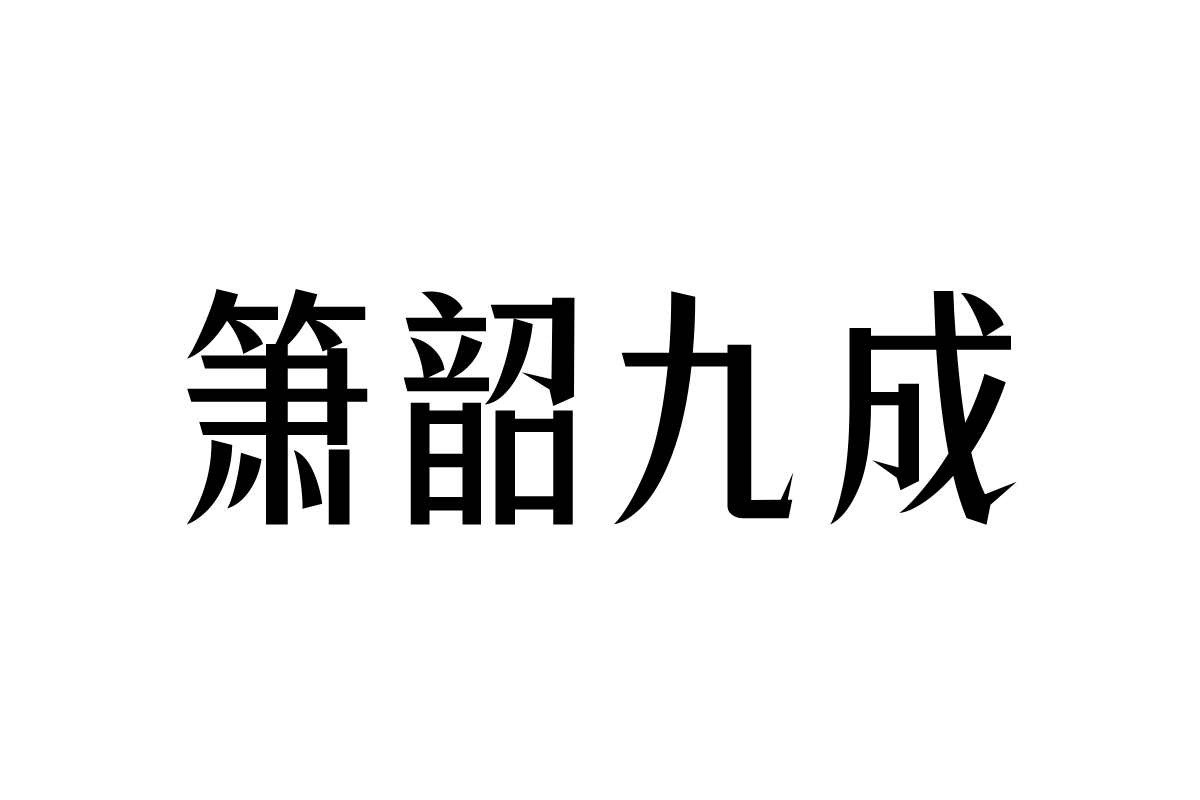
三极锐宋黑简体是一种中文字体,它由三个部分组成:粗体、中粗体和细体。这种字体的特点是笔画粗细适中,结构紧凑,易于阅读。
1. 粗体:这是三极锐宋黑简体的最粗版本,笔画粗壮有力,适合用于标题或强调文字。
2. 中粗体:这是三极锐宋黑简体的中等粗细版本,笔画粗细适中,既不会过于粗壮也不会过于纤细,适合用于正文文字。
3. 细体:这是三极锐宋黑简体的最细版本,笔画细腻柔和,适合用于需要细致表达的文字,如注释或说明性文字。
三极锐宋黑简体的特点在于它的简洁性和易读性,使得它在各种场合都能得到广泛的应用。无论是在报纸、杂志、书籍还是网页设计中,它都是一个很好的选择。